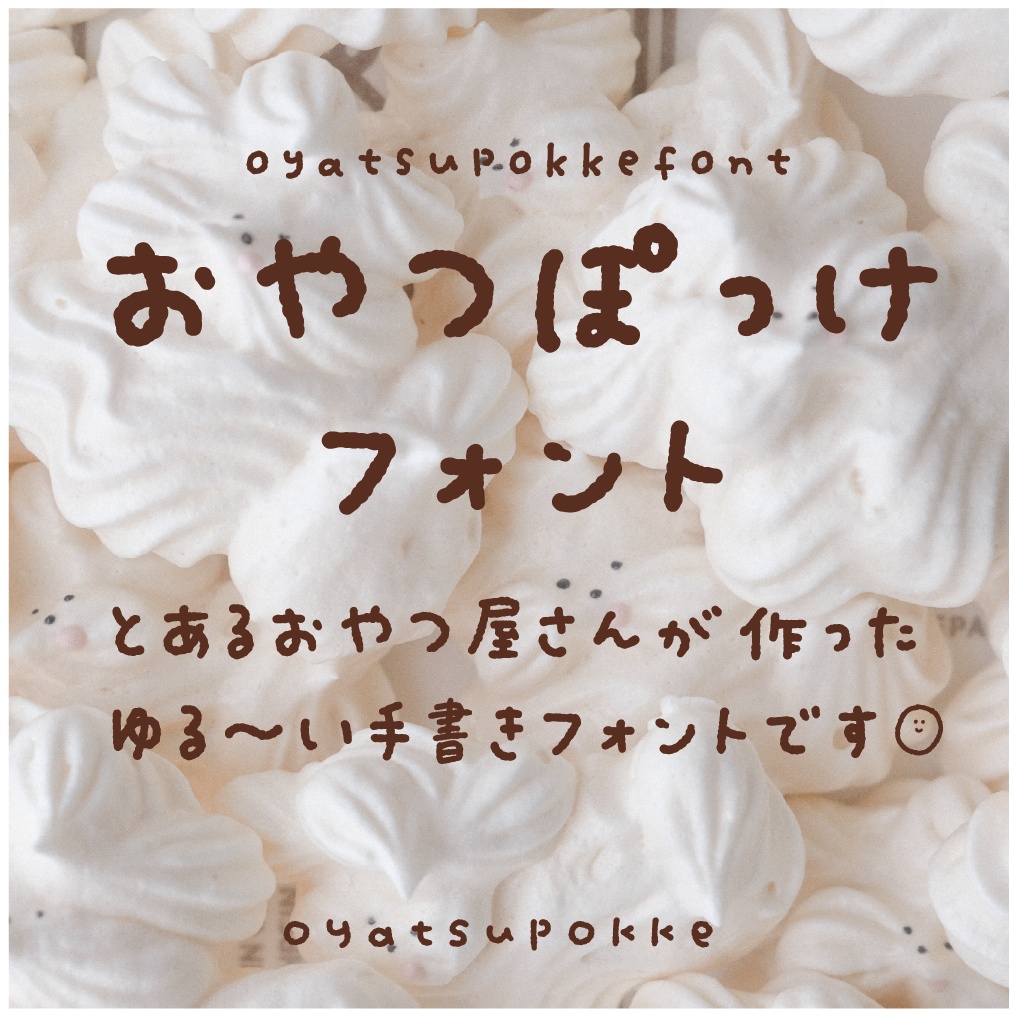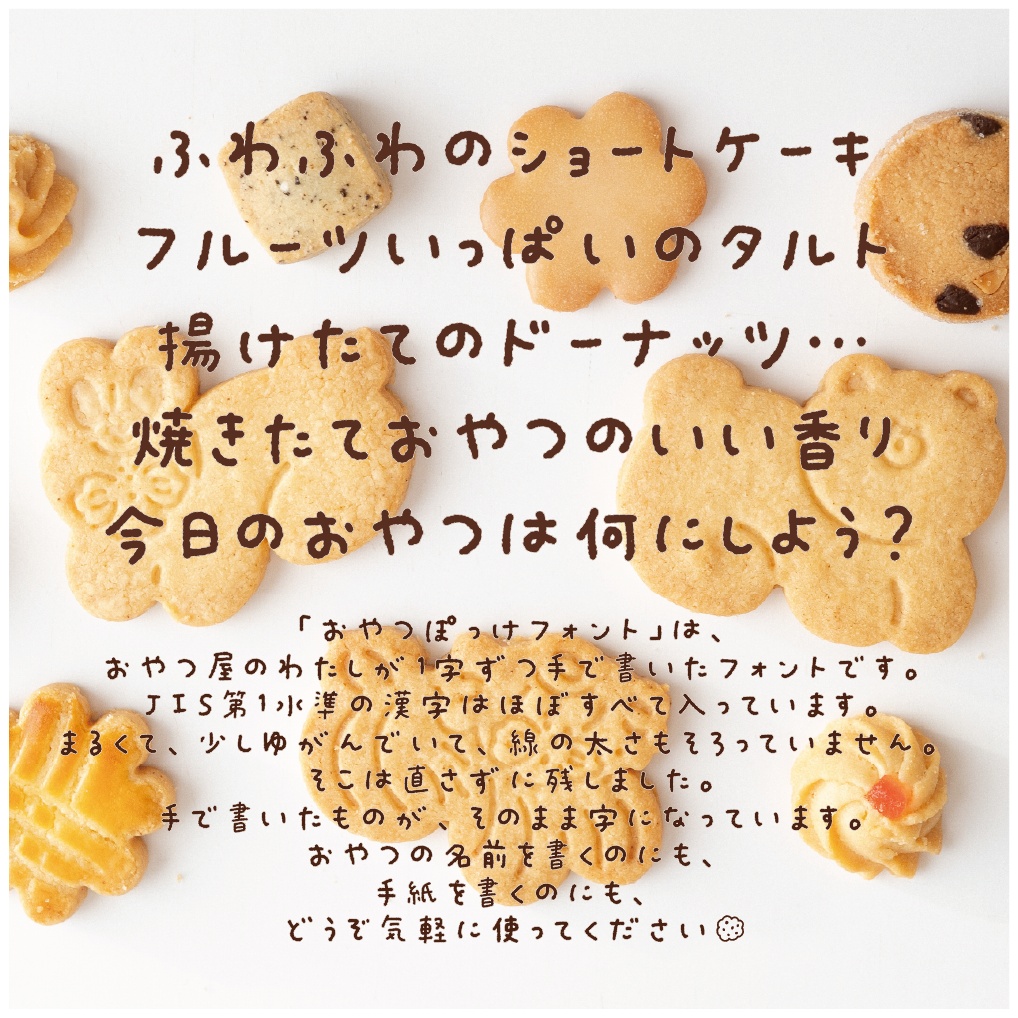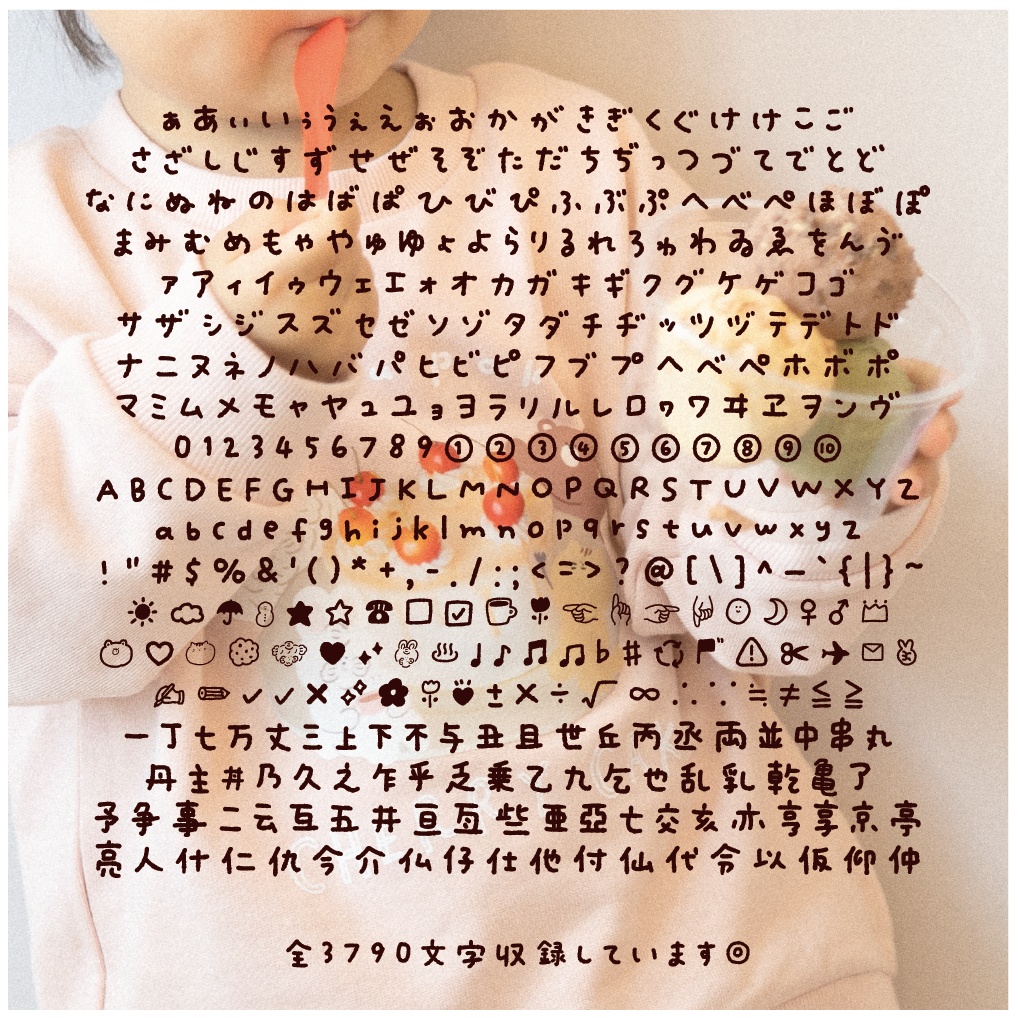
おやつぽっけフォント
とあるおやつ屋さんが作った、ゆる〜い手書きフォントです。 ________ 2026/8/14 更新(Ver 1.022)贅・仝・劃・竃・纂・廣・應・舖 を追加しました。 2026/8/11 更新(Ver 1.021):「げ」の濁点が抜けていたのを修正しました。 (凡ミスすみません・・・・) 8/11 22:05ごろより前にすでにダウンロードされた方はお手数ですが再ダウンロードをお願いします。 ________ 「おやつぽっけ」は、愛知県の洋菓子店 oyatsupokke の店主が、 1字ずつ手で書いて作った日本語フォントです。 まるくて、少しゆがんでいて、線の太さもそろっていません。 そこは直さずに残しました。手で書いたものが、そのまま字になっています。 お店の値札やPOPを書くためのフォントが作りたい、 というだけの話だったのですが、「この漢字がない」「この記号もほしい」と足していくうちに、 気づけば3,790字。JIS第1水準の漢字はほぼすべて入っています。 ________________________________ https://oyatsupokke.booth.pm/items/8962384 は投げ銭版です。 ダウンロードファイルは無料版と同じですのでご注意ください。 なにかのお役に立てた場合などに、投げ銭やBOOSTしていただけますと、大変励みになります! ________________________________ ■ 収録文字(全3,790字) ・漢字 3,048字(JIS第1水準ほぼ全部+旧字体・表外字84字) ・ひらがな 84字/カタカナ 90字(小書き・ゐゑ・ヴ含む) ・英数字・記号 188字(半角・全角) ・半角カナ 63字 ・アクセント付きラテン文字 60字(á é ü ñ ç など) ・約物・記号 約180字(★☆ →←↑↓ ♪♬ ☀☁☂☃ ♨☕✉☎ ♡ ✓ など) ・丸数字 ①〜⑩/単位記号 ㎏㎝㎜㎞㎡㍑㌘㈱㈲ ・手描きイラストいろいろ ■ 特徴 ・3,790字すべて手書き。機械生成や他フォントからの流用はありません ・字の形に合わせた自動カーニング入り。並べたときの見た目がそろいます ・Mac・Windows両対応(TrueType / .ttf) ・イラストは「とらんぷ」(♤いぬ ♧うさぎ ♢ねこ♠︎くま) ■ ご利用について 個人・商用ともに【無料】です。クレジット表記・利用報告も不要です。 〈OKな使い方〉 POP・メニュー・チラシ・ショップカード・商品パッケージ・ラベル・SNS投稿・YouTube・動画・Web上の画像・広告・印刷物・クライアントワーク など 〈ご遠慮いただきたい使い方〉 ・企業名・店舗名・ブランド名等のロゴとしての使用、商標登録 ・フォントの文字そのものを主役にしたグッズ・商品の制作販売 ・フォントファイルの再配布・販売・改変配布 ・AI・機械学習の学習データとしての使用 詳しくは同梱の利用規約をご確認ください。 Webフォント・アプリ等への組み込み、ご不明な点は事前にお問い合わせください。 ■ 同梱ファイル ・oyatsupokkefont.ttf(フォント本体) ・README_はじめにお読みください.txt ・利用規約.txt ・見本画像 ■ SNS 使っていただいた作例を見るのが一番の楽しみです。 よければ #oyatsupokkefont を付けて投稿してください。 ■ oyatsupokke について 愛知県にあるおやつ屋さんです。 お菓子だけでなく、イラストやパッケージも自分たちで作っています。 このフォントをきっかけにoyatsupokkeを知っていただけたらうれしいです。 ________________________________ https://oyatsupokke.booth.pm/items/8962384 は投げ銭版です。 ダウンロードファイルは無料版と同じですのでご注意ください。 なにかのお役に立てた場合などに、投げ銭やBOOSTしていただけますと、大変励みになります! ________________________________ 公式サイト:https://oyatsupokke.com/ Instagram:https://www.instagram.com/oyatsu_pokke/ ONLINE SHOP:https://oyatsupokke.shop-pro.jp/ 制作ストーリー(note):